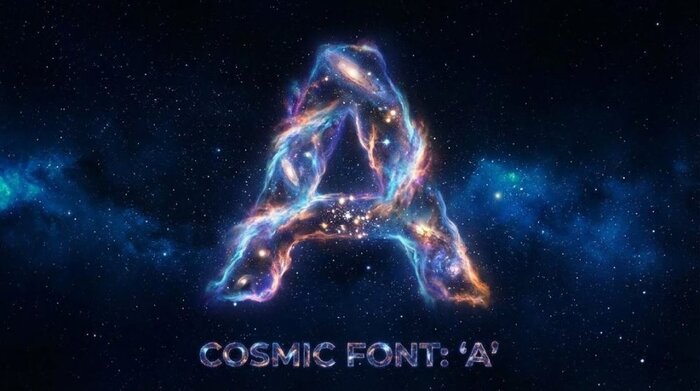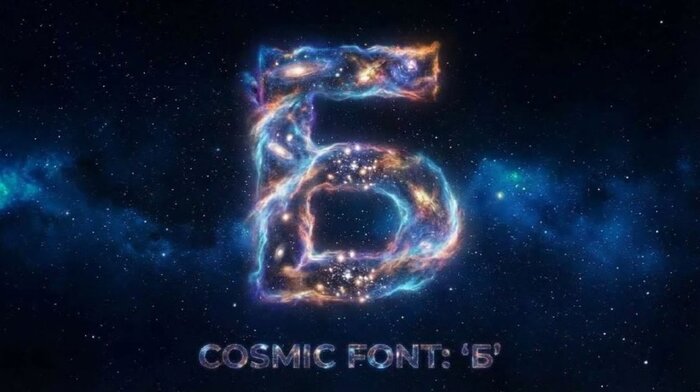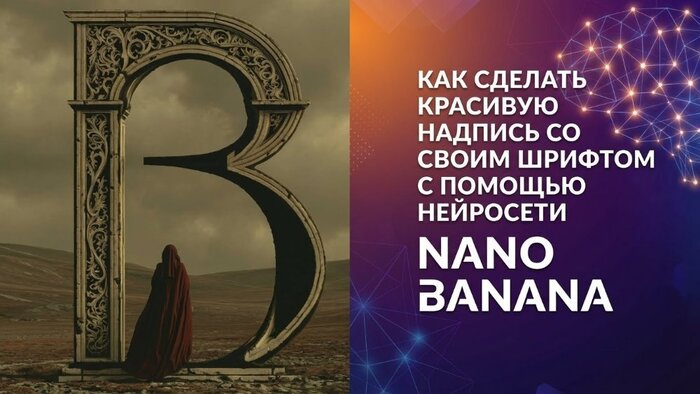
Сегодня создать авторский шрифт через нейросеть может каждый — не нужны специальные знания или навыки. Просто загрузите картинку с понравившейся буквой, нейросеть распознает стиль, после чего предложит целый алфавит в выбранном дизайне. Такой подход открывает простор для экспериментов: можно пробовать разные варианты букв, создавать декоративные заголовки, оформлять нестандартные подписи для соцсетей, элементы фирменного стиля и даже собирать свои TTF-файлы. Главное — понять схему работы с нейросетью.
В этом обзоре вы найдете не только подробную инструкцию, но и узнаете, как сделать красивую надпись быстро: от разработки логотипа до создания мерча и визуальных идей для бренда.
Для запуска процесса достаточно загрузить одну букву — нейросеть улавливает индивидуальные черты оформления и воспроизводит их во всех новых символах. Такой способ отлично подходит для творчества и решения бизнес-задач: оформления айдентики, создания фирменного стиля, рекламы. Далее — подробная инструкция.
Шаг 1. Заходим в Yes Ai Bot с Nano Banana Pro.
Шаг 2. Формулируем текстовое задание для генерации изображения. Например, можно указать одну крупную букву или составить промт:
Изобрази русскую букву [нужная буква] в [выбранном стиле], используется для создания шрифта.
Шаг 3. Дожидаемся результата и сохраняем картинку.
Чтобы получить серию букв в едином стиле:
Шаг 1. Открываем Nano Banana Pro.
Шаг 2. Загружаем изображение буквы и добавляем промт:
Сохрани стиль, нарисуй русскую букву [нужная буква].
Шаг 3. Выбираем функцию "Референс изображения".
Получаем новую букву и продолжаем формировать коллекцию.
Если удалось собрать хотя бы 30-40 разных символов, можно создать полноценный цифровой шрифт. Такой вариант отлично подойдет, если вы хотите добавить необычную типографику в собственный проект, не тратя время на ручную расстановку PNG-изображений.
Обычно минимальный набор включает:
26 латинских символов (A–Z);
33 кириллических (А–Я);
цифры, пробел и простые знаки препинания (. , ! ? - " ').
Даже если вы не планируете использовать все символы, наличие точки и чисел делают шрифт универсальным для большинства задач.
Важные параметры:
Единая высота (baseline и x-height);
Равномерная толщина линий;
Общий визуальный ритм и геометрия;
Аккуратные контуры без неровностей.
Инструменты для создания:
FontForge — бесплатный и простой;
Glyphs — подходит для пользователей macOS;
FontLab — функциональный, но требует опыта работы;
Calligraphr — отличное решение для старта без подготовки.
Нет необходимости собирать весь алфавит, если ваша задача — сделать надпись для логотипа. Часто достаточно 2–5 символов в одном стиле.
Где это особенно актуально:
Монограммы;
Логотипы и короткие фразы;
Оформление обложек, баннеров, интерфейсов.
Можно оставить буквы в формате растровых изображений, если их планируется использовать только на экране. Но для универсального применения лучше перевести буквы в векторный формат, чтобы сохранить четкость при любых размерах.
Если нейросеть помогла создать 10–15 букв в едином стиле, такой набор отлично подходит для эффектных заголовков. Даже неполный алфавит украсит визуальные посты или обложки, где главное — выразительность, а не объем текста.
Где можно использовать такой метод:
Стикеры и эмодзи для Telegram;
Презентационные заголовки;
Графика для сторис и новостных лент;
Оформление событий, афиш, digital-мерча.
В этих случаях нет нужды создавать полноценный шрифт: отдельные буквы легко применяются как изображения, вручную размещаясь в макетах. Такой способ идеален, если требуется получить эффектный результат максимально быстро.
Буквы можно сохранить в PNG, а для масштабирования без потери качества их легко перевести в SVG. Такой комплект прекрасно подходит для работы в Figma, Illustrator и других редакторах.
Нейросетевые буквы подходят не только для логотипов или шрифтов, но и как самостоятельные арт-объекты. Иногда их уникальность заключается именно в атмосфере, необычном стиле, игре с формой и фактурой. Из таких алфавитов создают полноценные серии — от плакатов до цифровых коллекций.
Такой подход пользуется популярностью среди художников и графических дизайнеров, особенно в рамках визуальных конкурсов и челленджей. Каждая буква превращается в отдельную иллюстрацию, сохраняя общий стиль, но раскрывая новые образы.
Варианты использования:
Плакаты, арт-книги;
NFT-коллекции;
Яркие визуальные заметки, сторис, креативные публикации.
В этом случае алфавит — не просто инструмент для набора текста, а способ для экспериментов с визуалом. Используйте растровые изображения, вручную оформляйте композиции, добавляйте текстуры, фон, детали. Такой метод отлично раскрывает индивидуальный стиль.
Если у вас есть 10–20 букв в едином стиле, не обязательно создавать полный шрифт. Каждая буква становится самостоятельным элементом — для мерча, постеров, принтов и цифровых проектов.